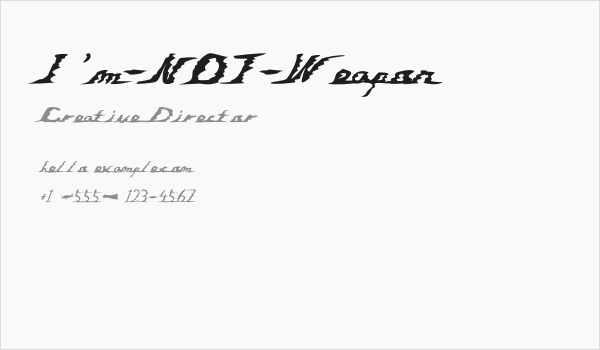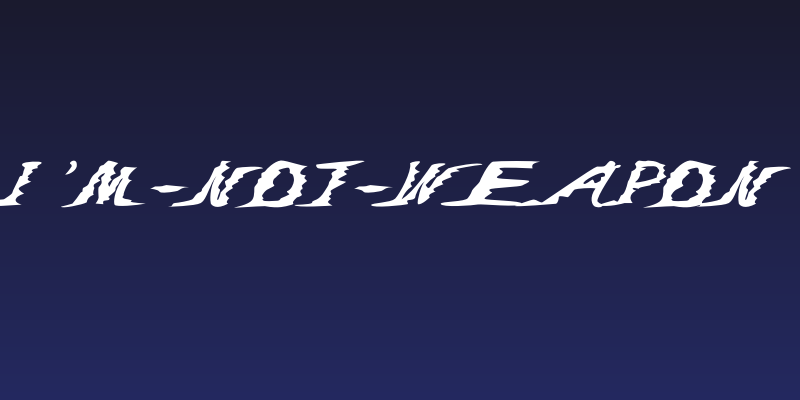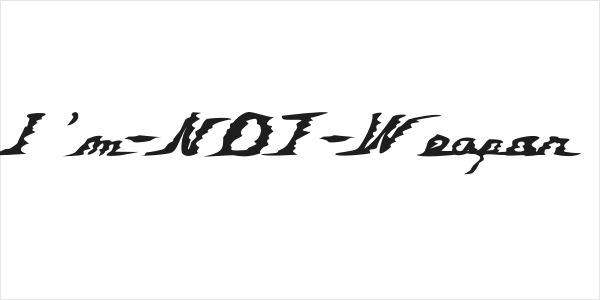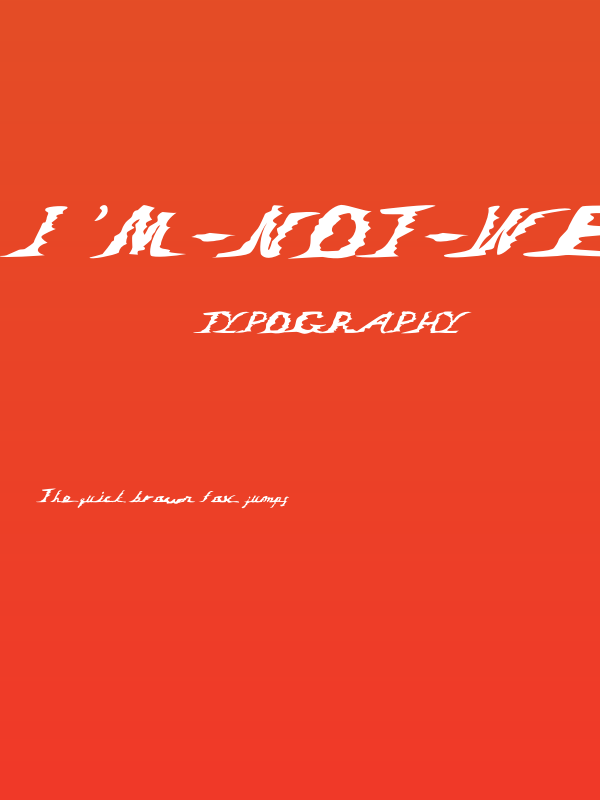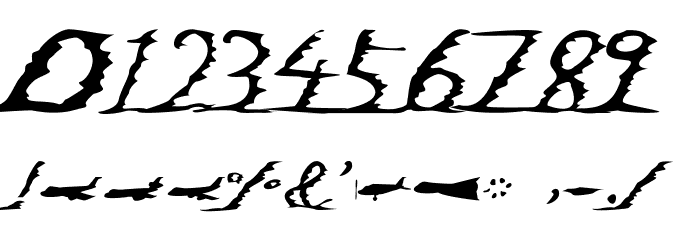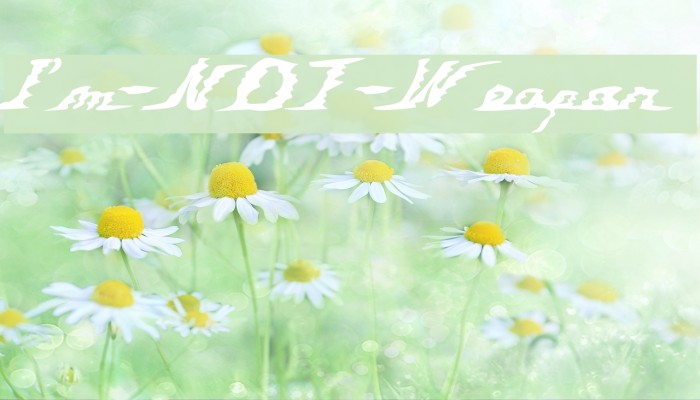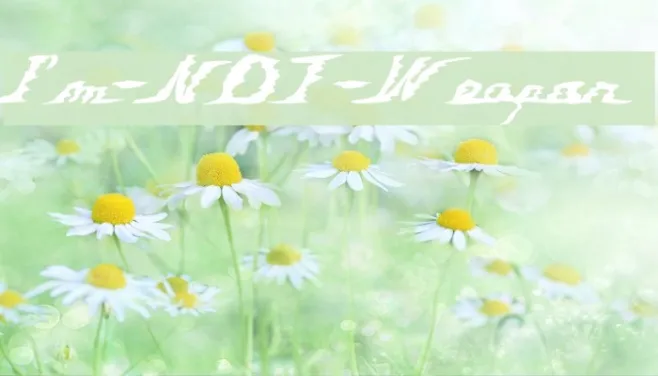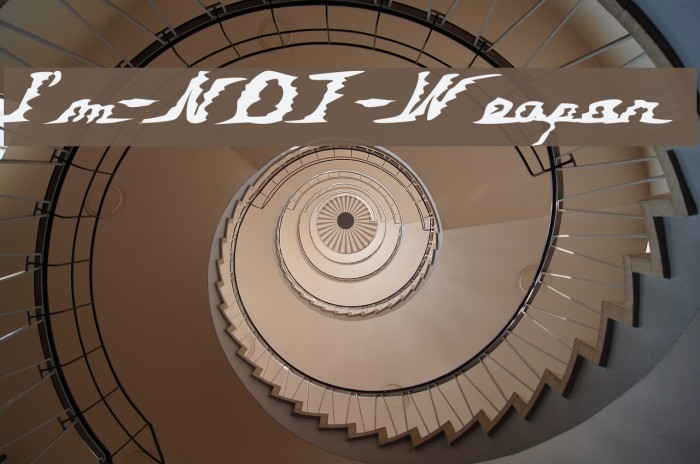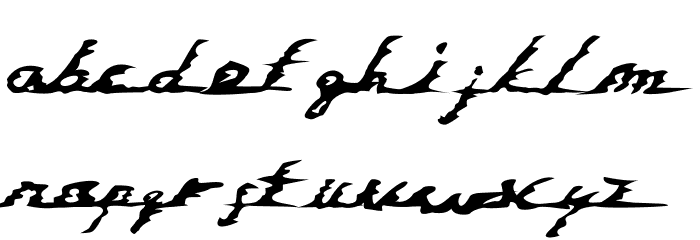
I'm-NOT-Weapon Font
Cette police comprend 15444 caractères. Cliquez sur un caractère pour voir les détails.
| Style général | Modern, Artistic |
| Cas d'utilisation | Headlines, Logos, Artistic designs |
| Projets proposés | Ideal for album covers, posters, graffiti art, or any project requiring a bold, artistic touch. |